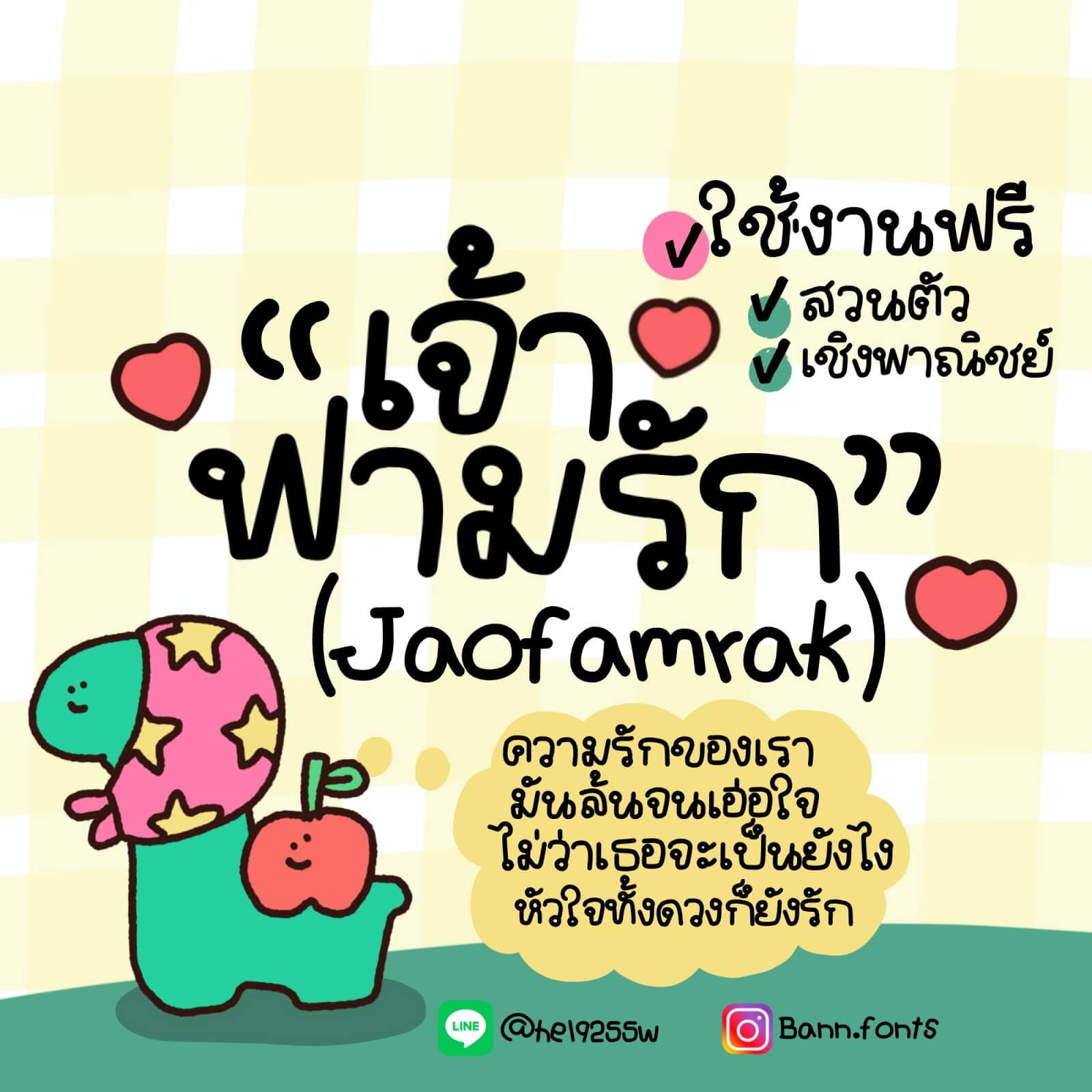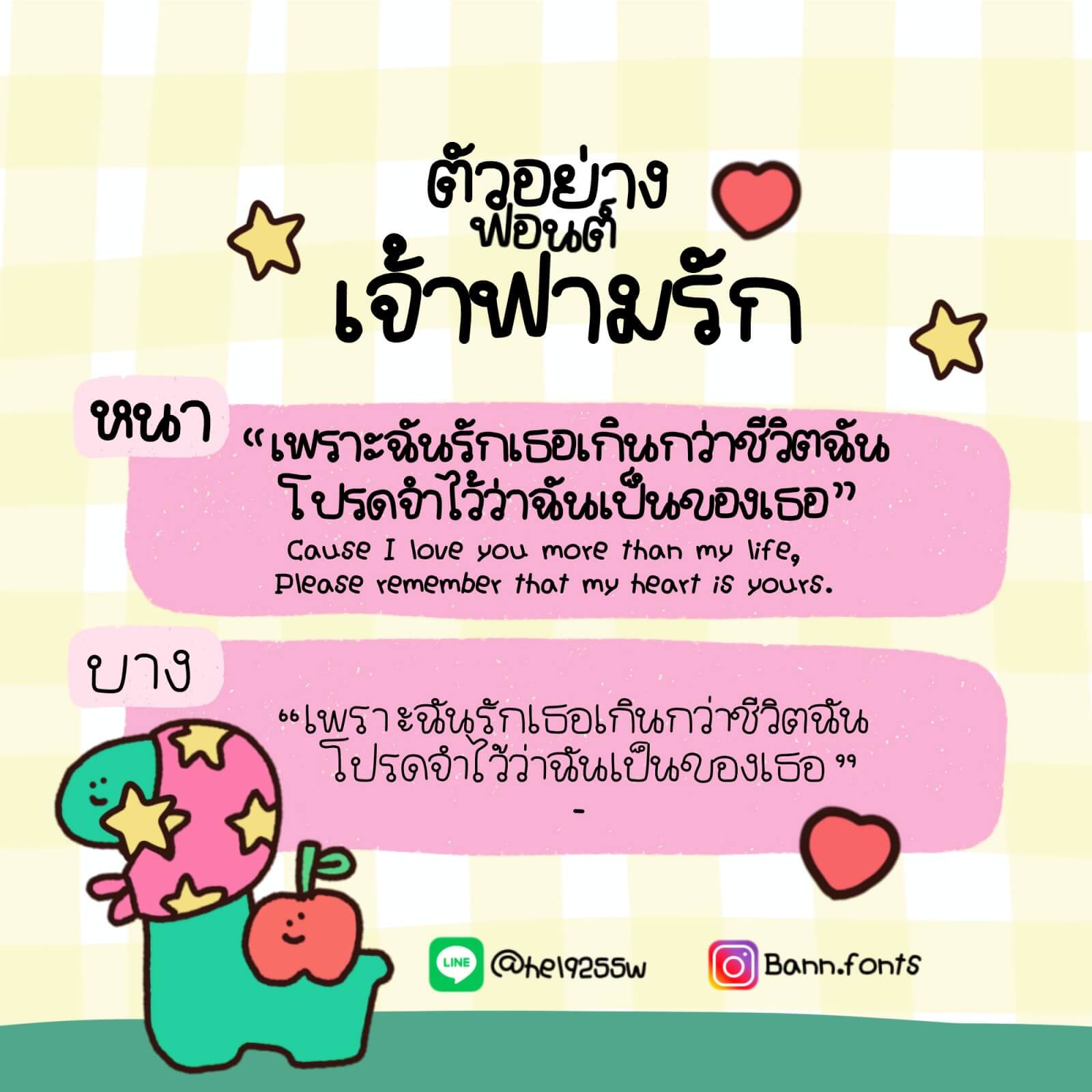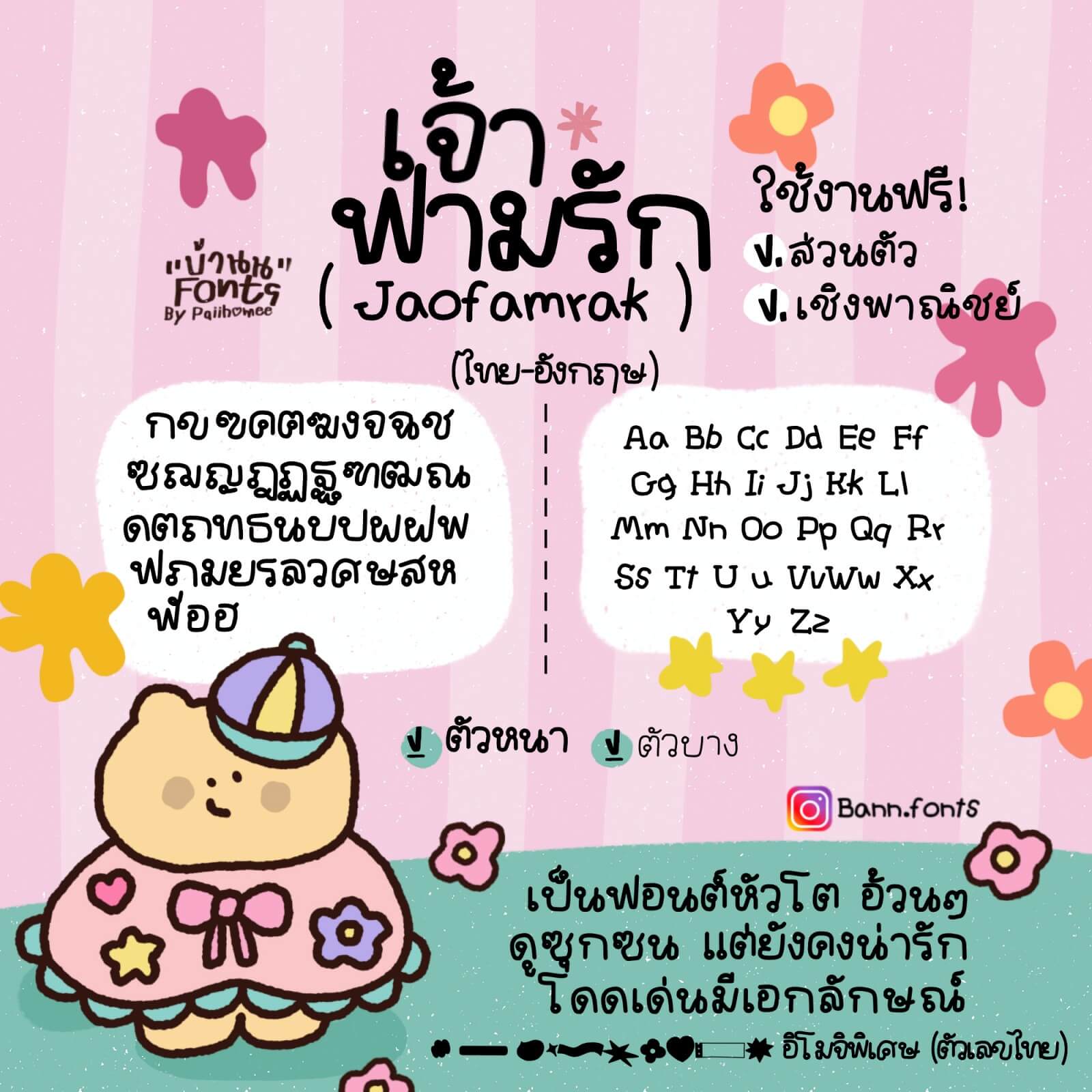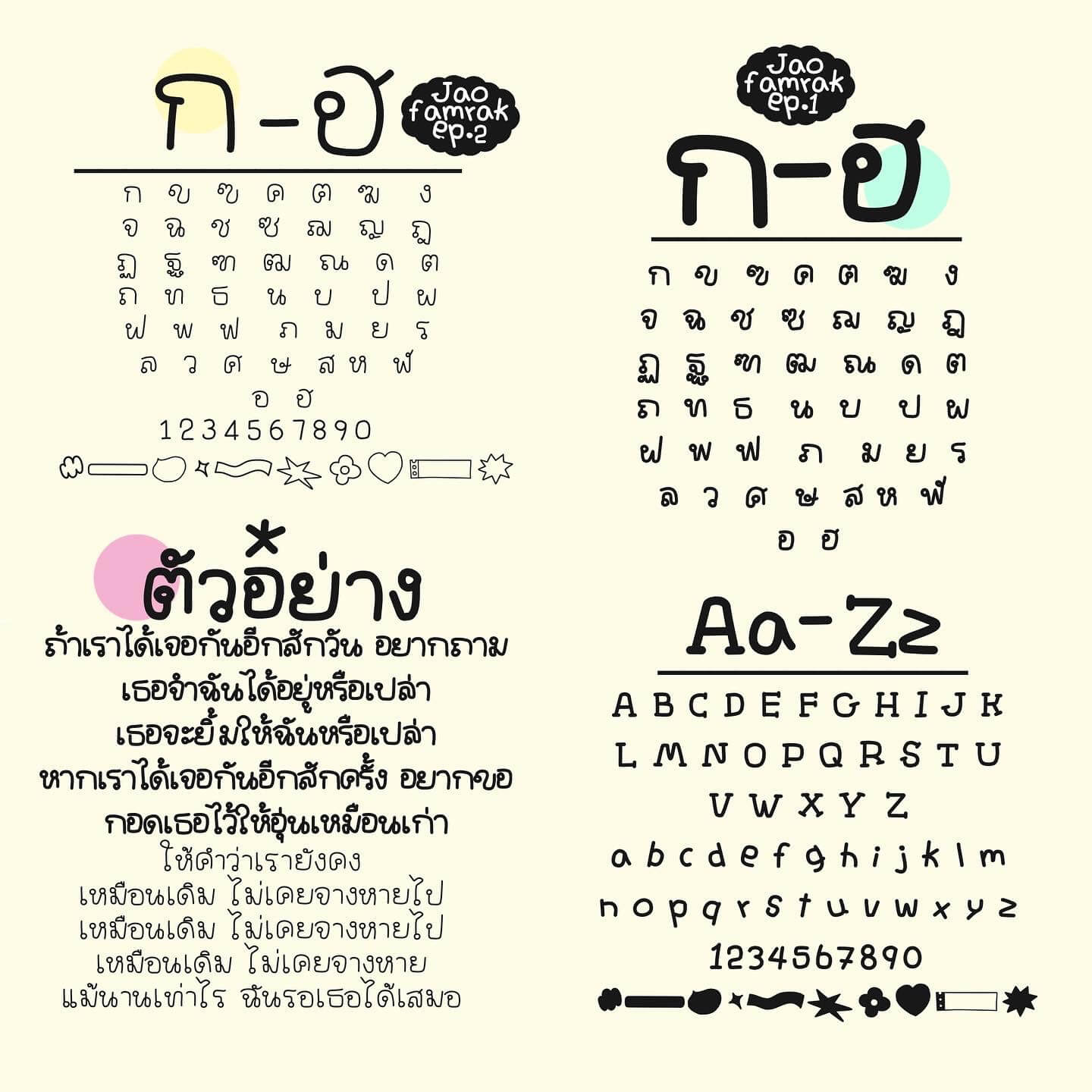
เจ้าฟามรัก (Jaofamrak)
ฟอนต์ เจ้าฟามรัก แจกฟรี! ✔️ใช้งานส่วนตัว & เชิงพาณิชย์ เป็นฟอนต์หัวโต ดูซุกซน แต่ยังคงน่ารักโดดเด่นเป็นเอกลักษณ์ มี 2 น้ำหนัก : เส้นหนาและเส้นบาง
เลขไทย (๐๑๒๓๔๕๖๗๘๙) เปลี่ยนเป็นอีโมจิไว้ตกแต่ง เพิ่มความน่ารักให้การใช้งาน